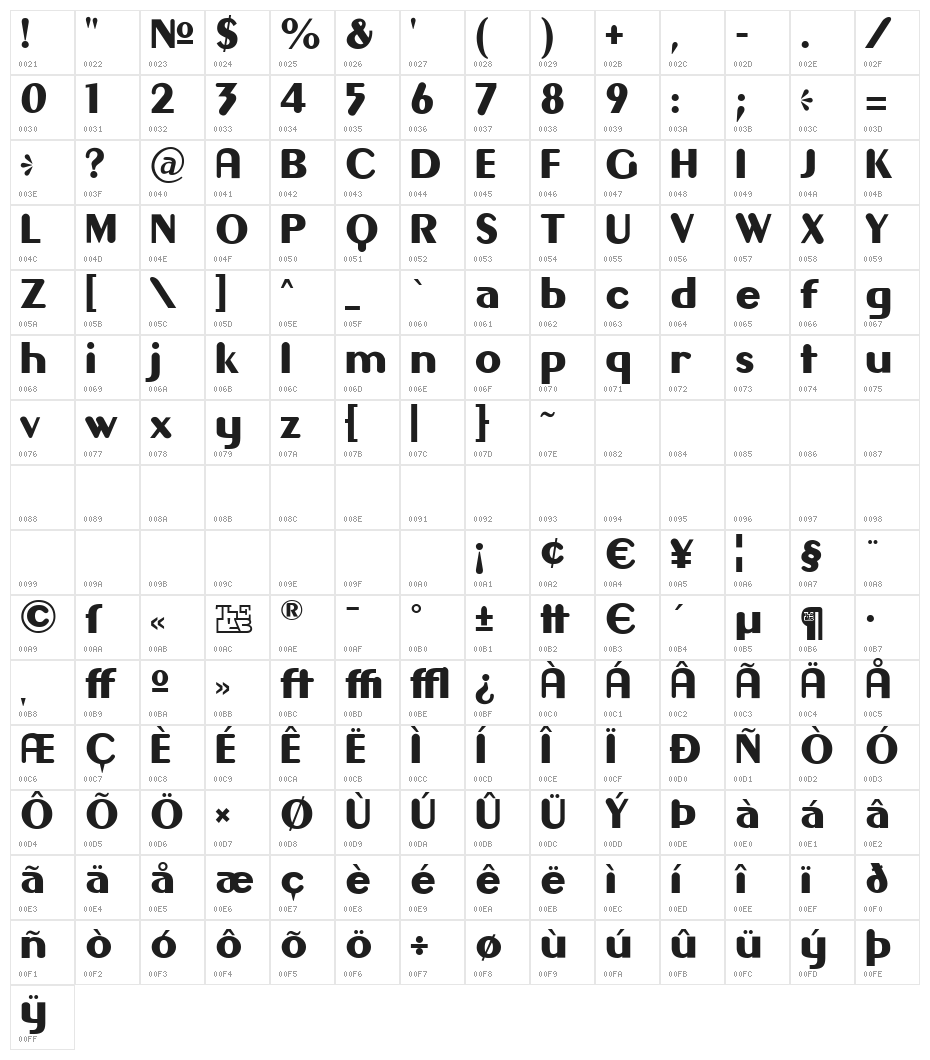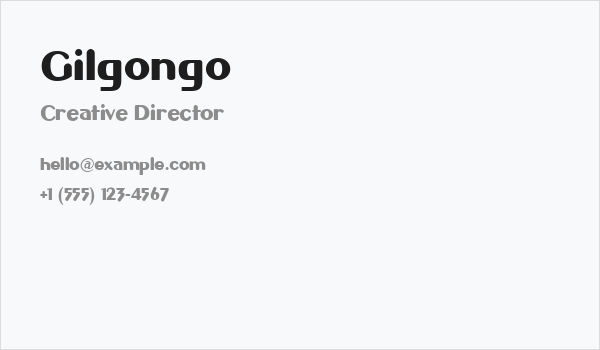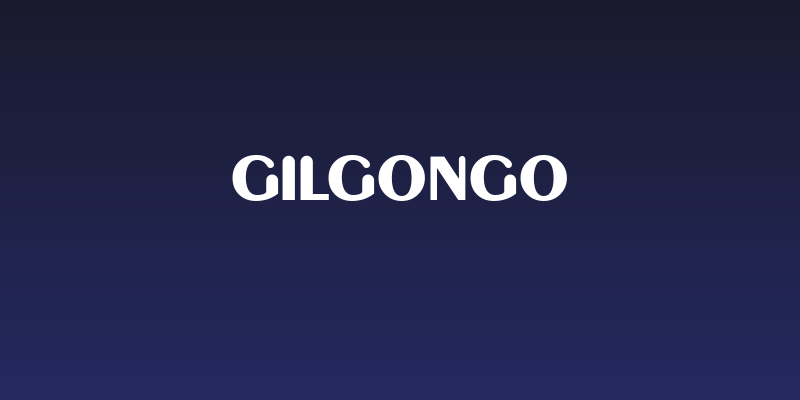
Gilgongo Font
| Vorgeschlagene Projekte | This font is perfect for modern branding projects, eye-catching headlines, advertising campaigns, and digital media where a strong, contemporary presence is needed. |